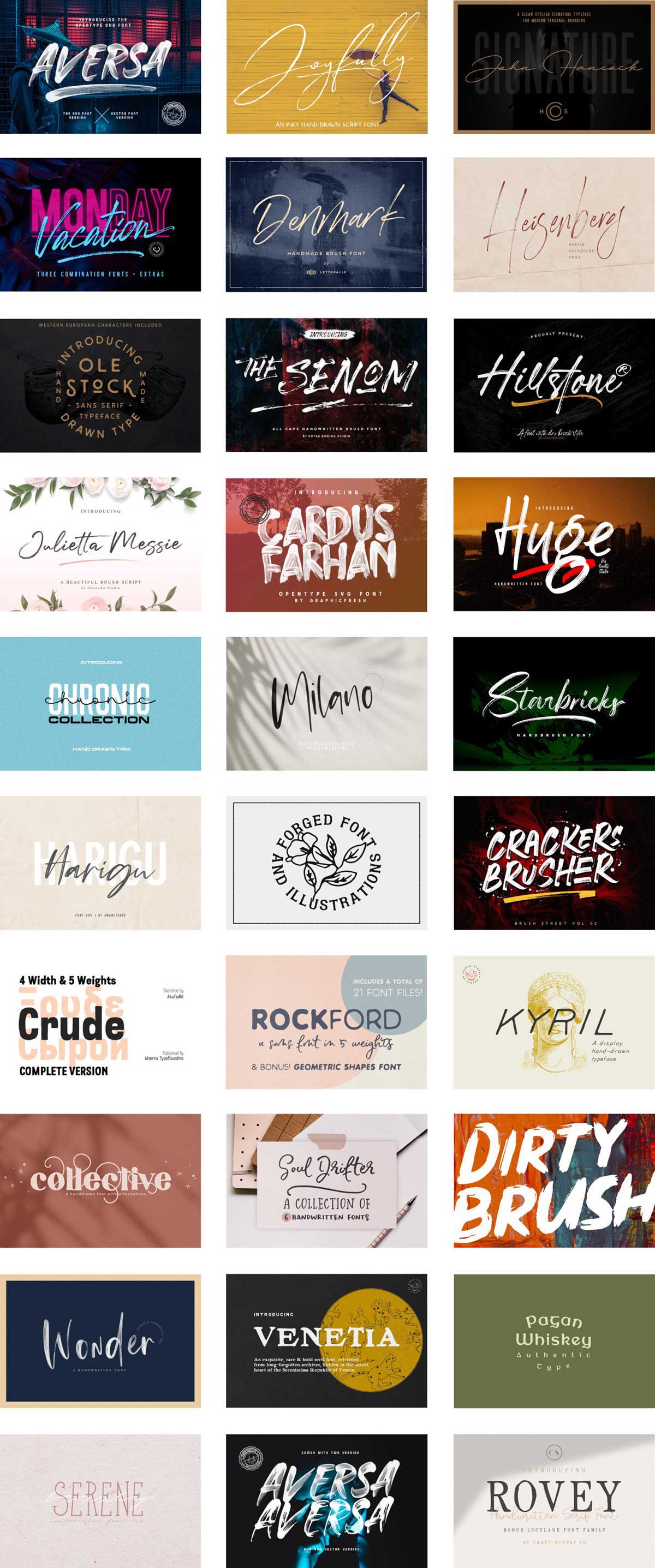
Pixel Surplusでは、フォント集「The Handmade Font Collection(ザ・ハンドメイド・フォント・コレクション)」が一ヶ月限定販売中です。
人気の手書き風書体29セットを収録したコレクションです。Pixel Surplusでしか買えないオリジナルフォントや、イラストやロゴテンプレートなどのおまけもたくさん入っています。
「The Handmade Font Collection」の気になる内容
今回のバンドルの中で、私が特に気になるフォントはこちらです。
Crackers Brusher – MLKWSN
かすれた風合いを忠実に再現した、ストリートアート風のブラシフォント。ポスターやフードメニューをはじめとした様々な媒体に利用できます。
John Hancock – Hustle Supply Co.
直筆サインをそのままフォントにしたような「John Hancock」。手書き風ですがクリーンな印象なので、ブランディングやロゴデザインにも適しています。
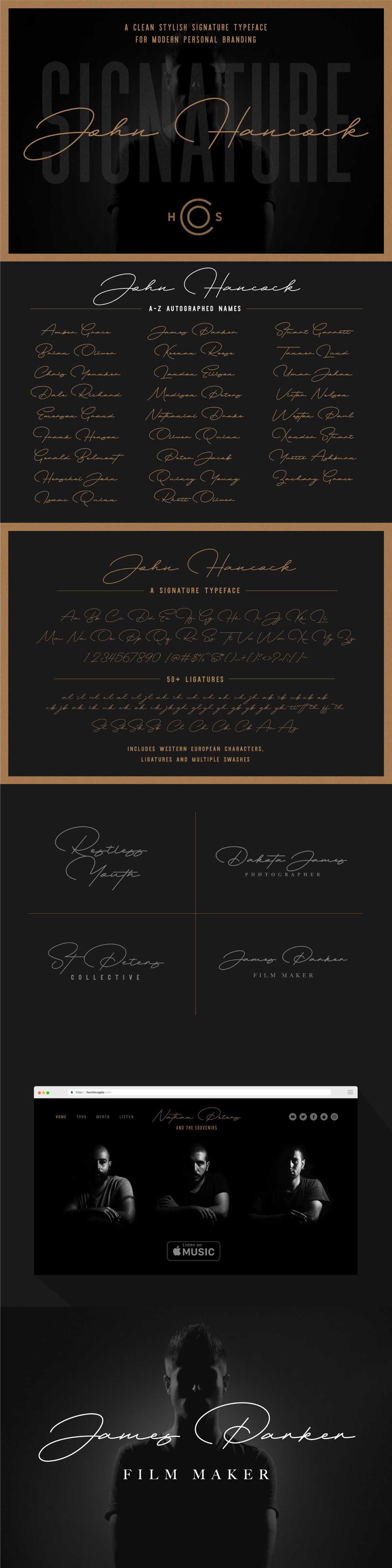
Rovey – Craft Supply Co.
ところどころいびつで味のある「Rovey」は、使うだけで簡単にハンドメイド感を演出できるフォント。スクリプトフォントつきなので、組み合わせて使う書体をわざわざ探さなくていいのが便利です。
Joyfully – Pixel Surplus
「Joyfully」はPixel Surplusオリジナルの手書き風スクリプトフォント。Pixel Surplusでしか手に入らないフォントも、このバンドルに収録されています。
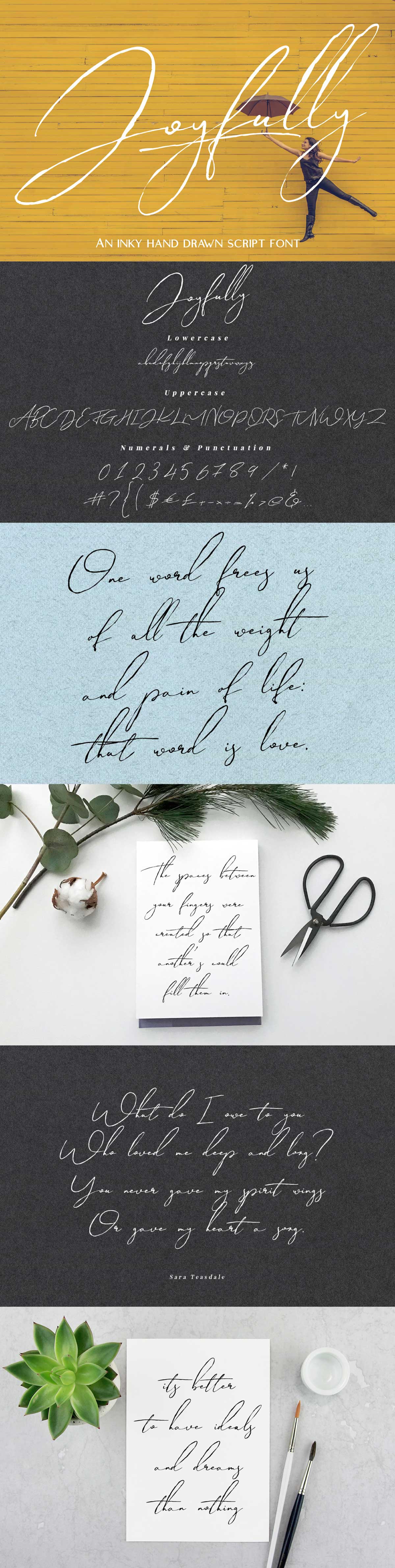
Aversa – Graphicfresh
かすれ始めたポスターカラーマーカーで書いたかのようなSVGフォント「Aversa」。フォトショップのブラシつきでお得です。